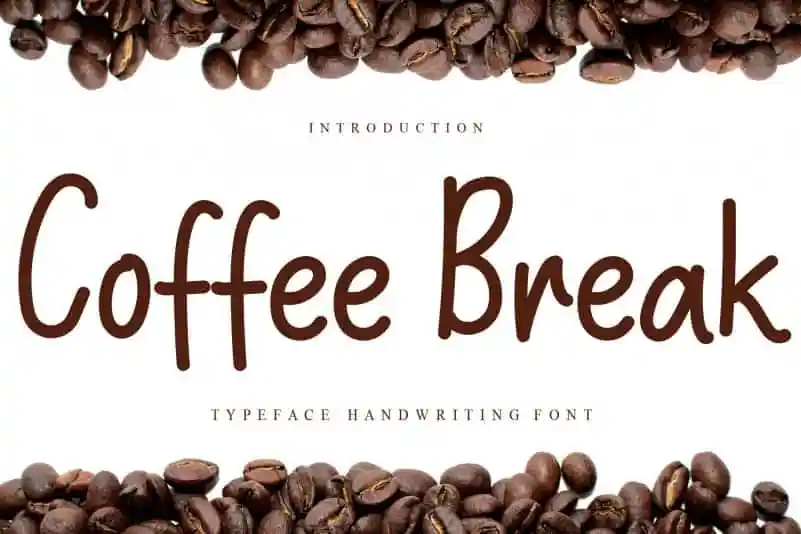
Coffee Break Script Font – Download Grátis
Aqui está uma descrição para a página de download da fonte ‘Coffee Break Script Font’, mantendo-se fiel ao gênero informacional sem inventar características ou alterar o tom: O Coffee Break Script Font é um tratamento handwritten que traz uma vibe descontraída e autêntica, perfeito para adicionar personalidade a qualquer projeto. Especialmente ideal para designers buscando uma fonte leve e relaxante, essa família de negrito e itálico vai dar um toque único a seu trabalho. Introduzido pela equipe da andikastudio, o Coffee Break Script é projetado para proporcionar experiências únicas e criativas. Com seu estilo elegante e fluido, ele se adapta bem a aplicativos como letras em cartões de felicitações, designs digitais personalizados ou mesmo escrita manuscrita no papel. O resultado final é uma fonte que vai trazer um toque especial a qualquer projeto visual, tornando-o ainda mais autêntico e divertido. A andikastudio criou uma fonte específica para quem deseja dar um toque único em seu trabalho sem comprometer a qualidade ou legibilidade. Experimente essa fonte handwritten única no Coffee Break Script Font, e veja como ela transforma o visual de seus projetos digitais.